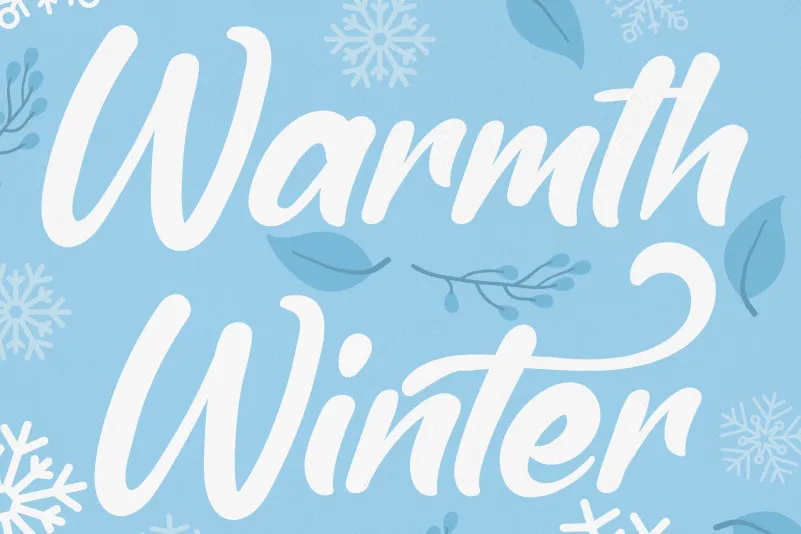
A Warmth Winter Script Font é uma elegante fonte criada com a delicadeza de um belo canuto. Essa fonte tem traços fortes e encantadores, feitos para capturar o espírito quente do inverno. Perfeita para diversas aplicações como logotipos, convites para casamento, títulos, camisetas personalizadas, cartões de visita, sinalização, etiquetas, notícias, panfletos e até mesmo emadidos. É uma fonte ideal para aqueles que desejam um toque quente e elegante ao decorar suas criações gráficas. Warmth Winter Script Font é o alicerce perfeito para qualquer projeto de design visual.